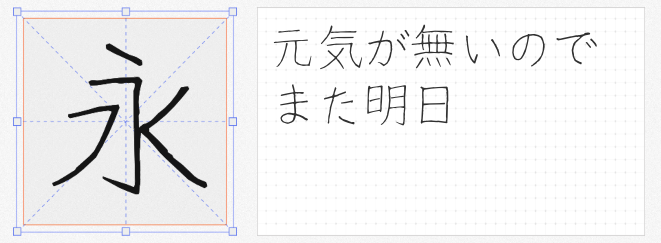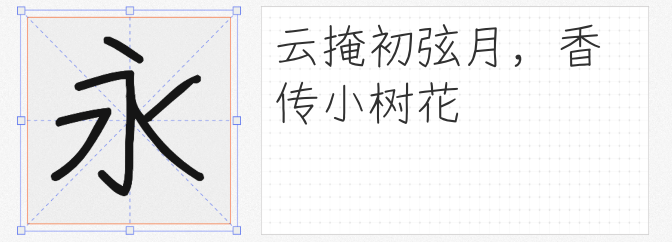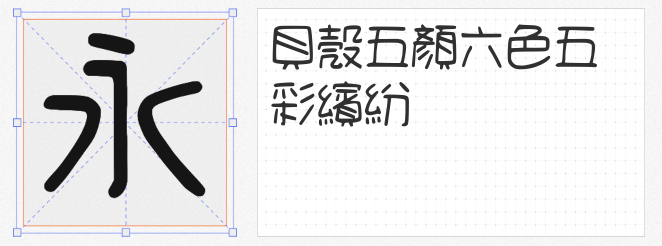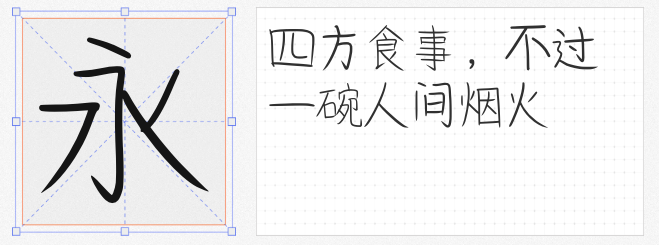
在设计中,字体选择至关重要,尤其是手写风格的字体,能够赋予作品独特的个性和温度。今天,我们为大家推荐四款可免费商用的手写字体,它们各具特色,适合多种设计场景。
1.Acy手写体
Acy手写体由国内知名设计师lxfly2000亲自打造,这款字体是在他B站FontForge视频教学过程中放出的惊喜。Acy手写体共有三款字重,从轻盈到厚重,满足了不同设计需求。它的线条流畅自然,既有手写的随性,又不失设计的精致感,是海报、邀请函等设计的绝佳选择。
2.细鸣字体
细鸣字体以其纤细的线条著称,共有三种字重,能够轻松应对各种设计场景。无论是清新的网页文案,还是精致的宣传册,细鸣字体都能以其独特的韵味吸引眼球。它的设计简洁而不失优雅,为作品增添了一抹文艺气息。
3.悠哉字体
悠哉字体基于Y.OzFont的手写风格,设计师巧妙地利用原字体中的笔划和部件,通过拼接和调整创造出新字。必要时,设计师还会亲自用鼠标绘制部件,以确保字体的统一性和美观性。悠哉字体共有三款字重,每一款都充满了手写的韵味和设计的匠心。
4.清松手写体4
清松手写体系列由游清松在稿纸上用原子笔手写而成,透过「守写字」网站产生初稿字型档,再经过字型软件后制加工而成。清松手写体4是该系列中的一款佳作,其风格独特,既有手写的随性自然,又不失设计的严谨和精致。这款字体适合用于笔记、日记、书信等场景,也能为广告设计、包装设计等增添一抹独特的手写风情。
这四款免费商用的手写字体,各具特色,风格各异。无论是追求设计感的广告人,还是注重个性的文艺青年,都能在这些字体中找到心仪的选择。快来试试吧,让你的设计作品因这些独特的手写字体而更加出彩!